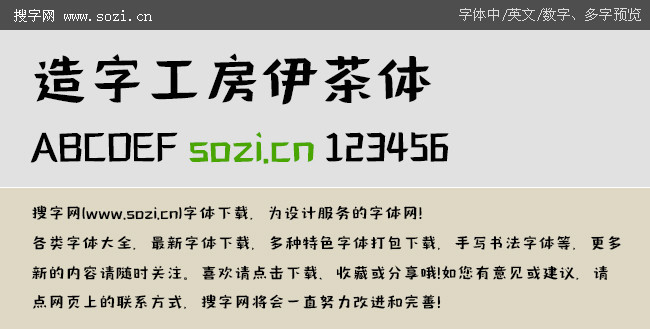
造字工房伊茶體
搜字網(wǎng)給大家提供一款造字工房伊茶體中文字體下載,造字工房伊茶體筆畫(huà)利落、鉤角凌厲,橫折處做斜切處理,雕琢精致,似茶葉中粗頭尖,使字形豐富靈動(dòng),游刃有余,賦予字體一種侘寂美感。適用于大標(biāo)題、包裝設(shè)計(jì)、海報(bào)設(shè)計(jì)等應(yīng)用。(本字體為個(gè)人非商用版,如需要商用請(qǐng)聯(lián)系官方購(gòu)買(mǎi)版權(quán))